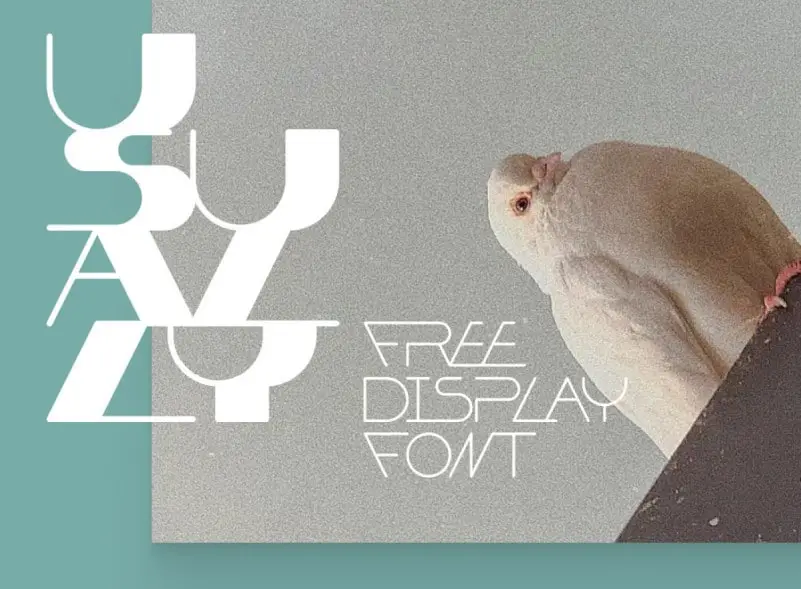
Usually Display Font – Download Grátis
Introduzimos a fonte Usually Display Font para você. Trata-se de uma tipografia em maiúsculas desenhada à mão com serifas clássicas e vintage, mas com um toque moderno. Este tipo especializado foi criado pelo design-font Alexey Atapin. Free para download, tem variações tanto regular quanto bold. As formas dinâmicas são ideais para posters, capas de álbuns ou qualquer outro uso que exija destaque visível e atraente. Usualmente Display é uma escolha perfeita para estabelecer um visual moderno com toques de nostalgia clássica. Experimente incorporá-lo em sua próxima peça gráfica, seja ela uma camisa de manga curta ou um logotipo de marca.